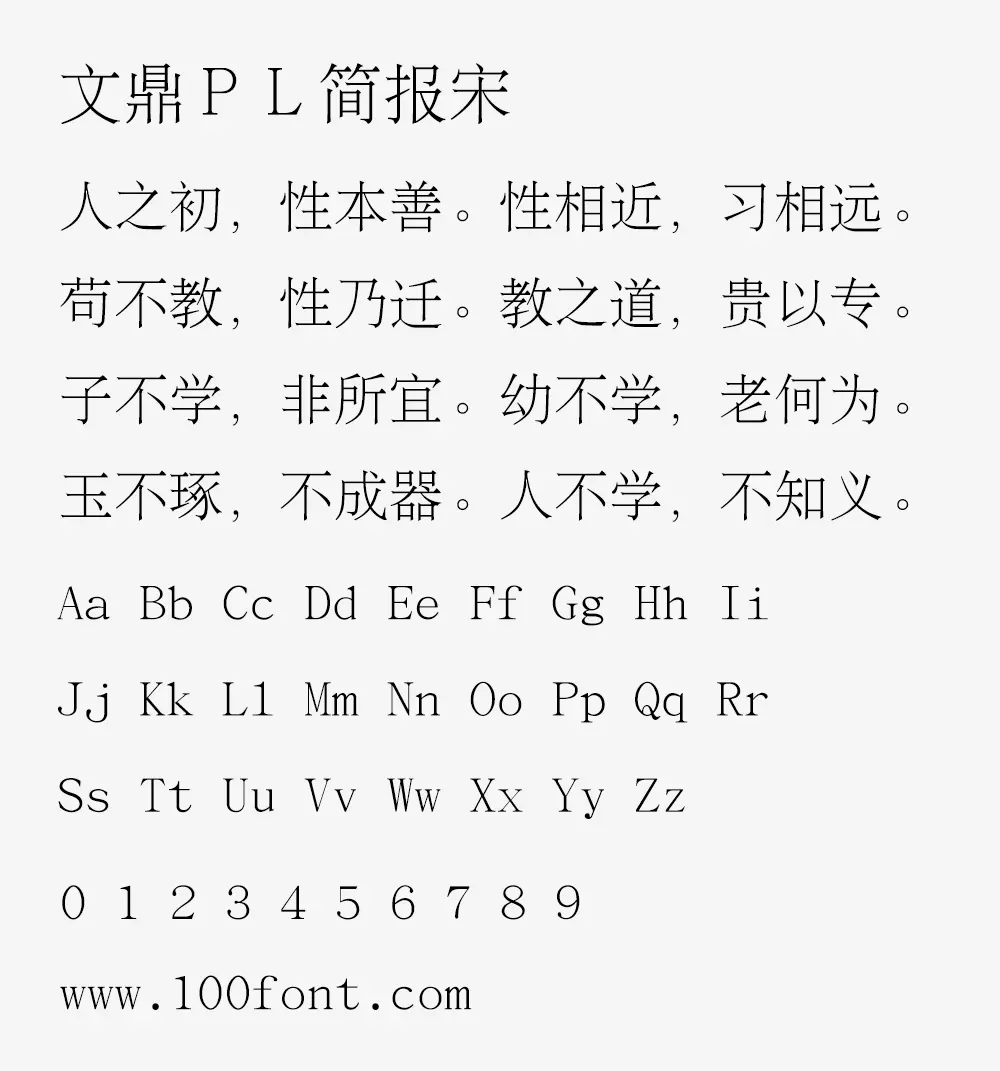
基於支持 Linux 與自由軟件發展的立場, 文鼎科技熱心的提供了四套開源免費中文 TrueType 字體(文鼎PL細上海宋、文鼎PL簡報宋、文鼎PL中楷、文鼎PL簡中楷)供大家自由使用,更可貴的是,該公司以類似 GPL 的版權釋出字體、完全開放字體供人複製與修改,這種作為在目前軟件廠商中是很少見的,這四套字體對整個中文環境的架構有很大的幫助。